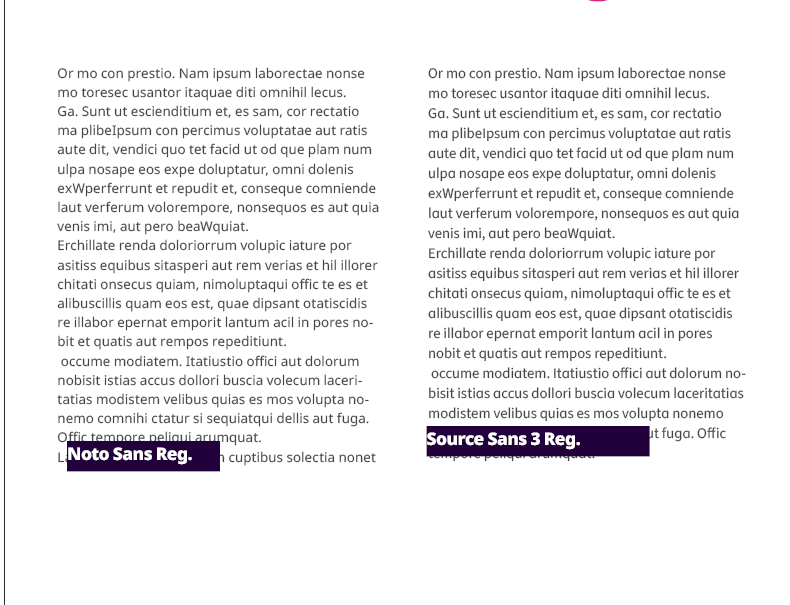
Noto Sans: Alternative oder Fließtext-Paarung
Hallo, ich finde die Noto Sans für Titel sehr cool. Allerdings mag ich die Schrift für Fließtext nicht. Irgendwie wird sie "schwammig" und unscharf, wenn sie nicht extrem kontrastreich ist.
Jetzt suche ich entweder eine ähnliche Titel-Schrift als Noto Sans-Ersatz oder eine neue für Fließtextschrift zur Paarung mit eben dieser. Ich mag z. B. das Schriftbild der Greycliff CF, denke aber, die ist nicht so passend oder?
Danke, ja. Hatte ich schon getestet. Ich sollte noch ergänzen: Es soll ein "plakatives" Portfolio (Fließtext in Blocksatz) werden und ich weiß nicht, ob eine Serif zu spießig wirkt?
Nur eine Überlegung:
Die Noto Sans gehört inzwischen zu den ich sag mal charakterlosen, neutralen Allerweltsschriften wie Helvetica. Das kann bei einem Portfolio passen, wenn man die Arbeiten in den Fokus stellen will.
Wenn Du aber auch eine persönliche Note ausdrücken willst, würde ich generell nicht zur Noto greifen, sondern etwas eigenständigeres, unverbrauchteres wählen.
Das könnte dann zum Beispiel so etwas sein: